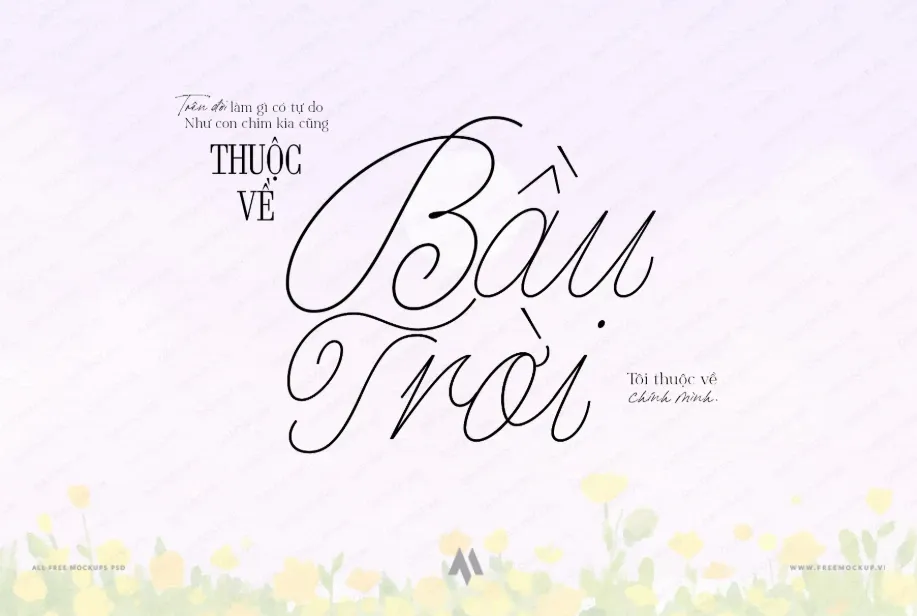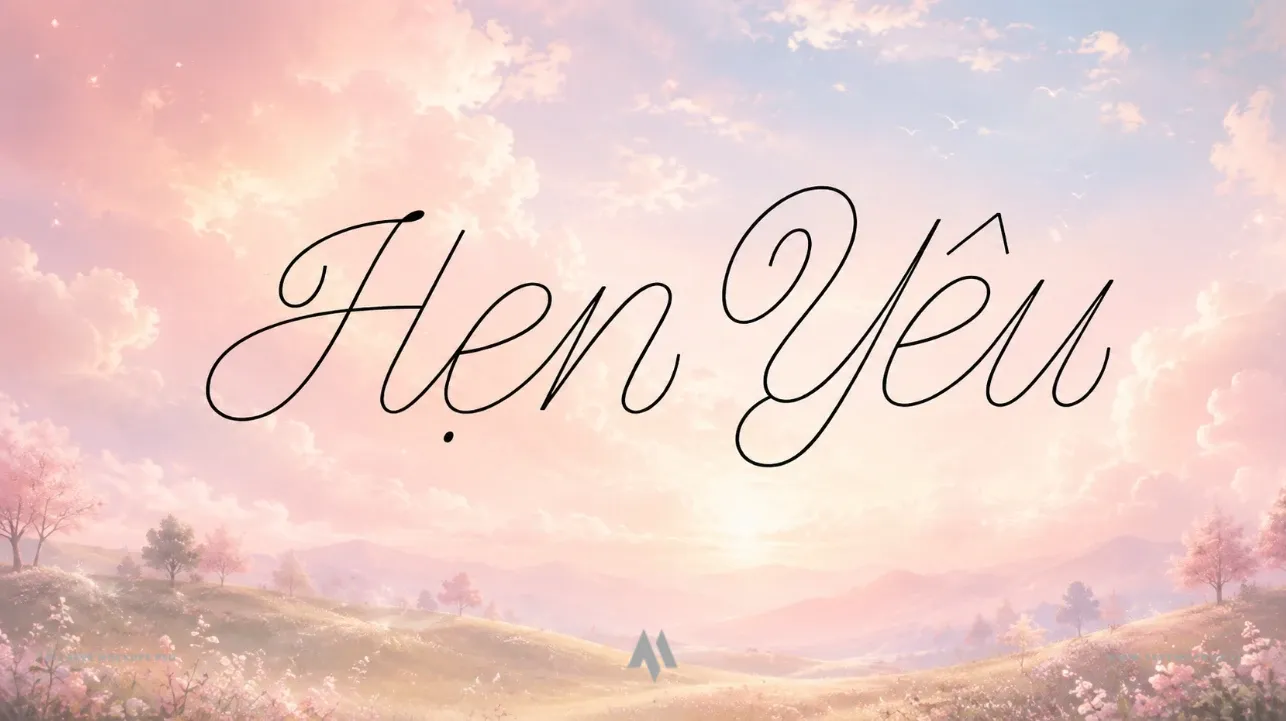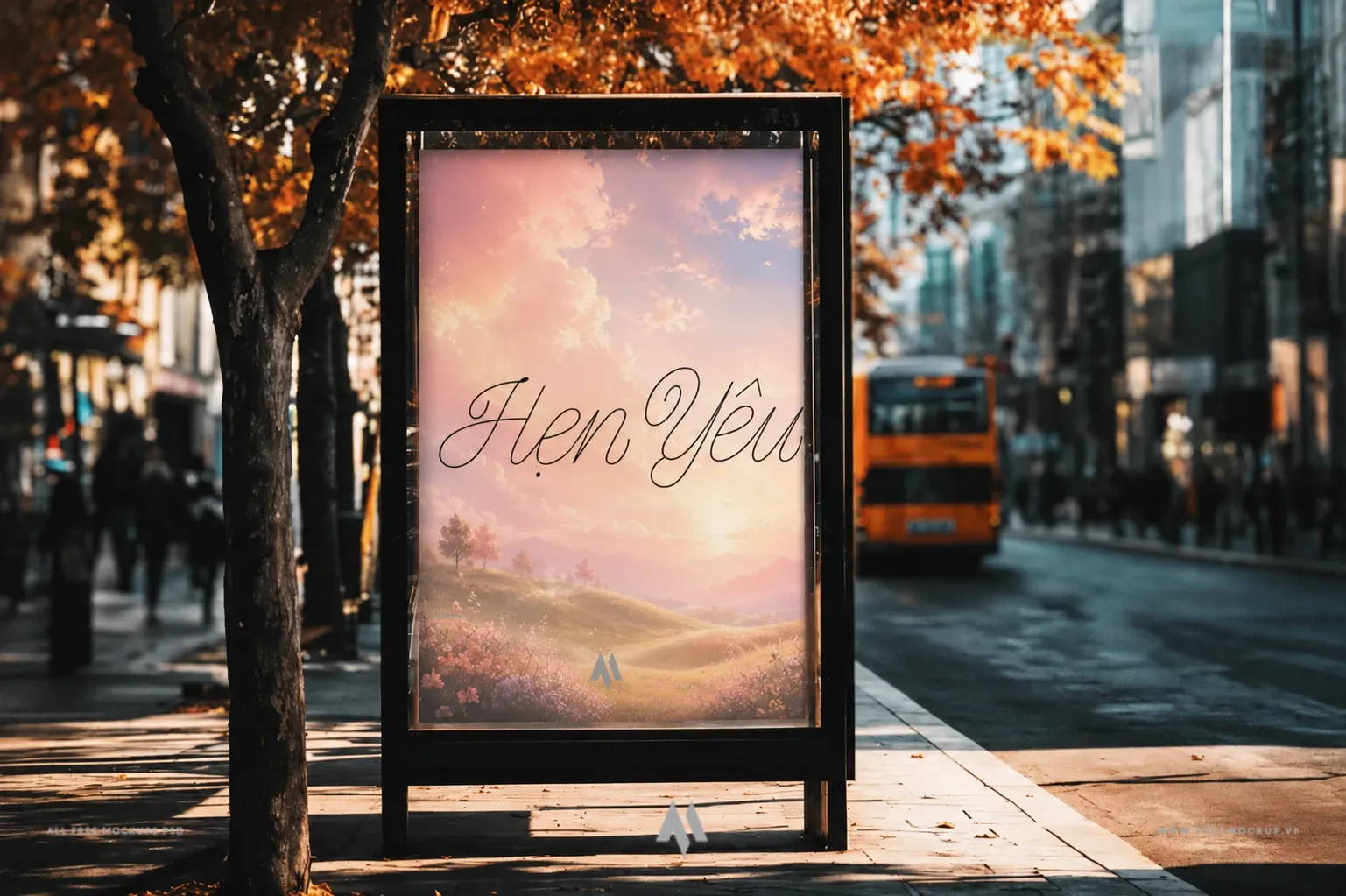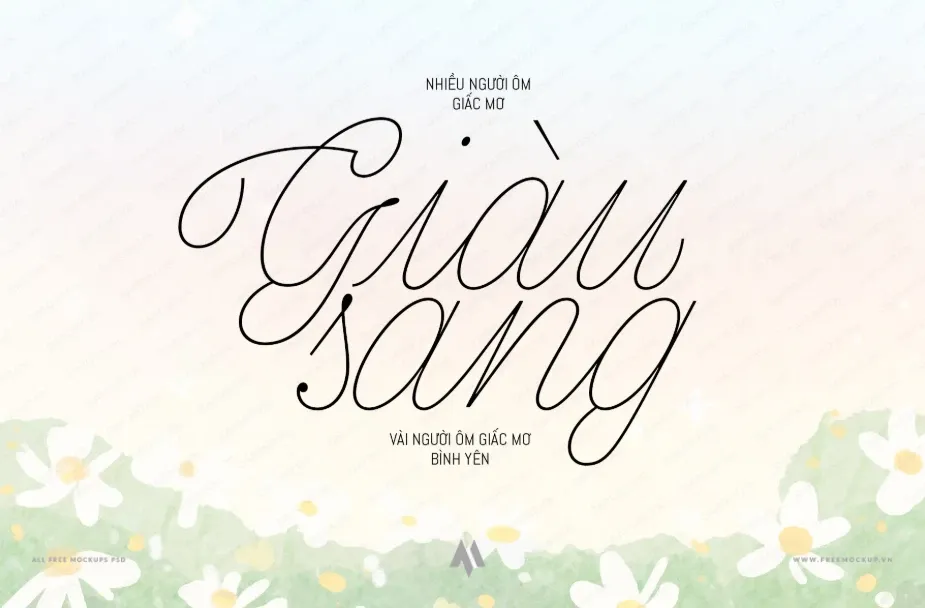
Font viết tay Việt hóa DFVN Pencerio
DFVN Pencerio Việt Hóa là bộ font chữ viết tay trang trọng (Formal Script) được thiết kế bởi xưởng font danh tiếng Indian Type Foundry. Lấy cảm hứng từ nghệ thuật thư pháp Spencerian kinh điển nhưng được cách tân độc đáo, Pencerio lược bỏ độ tương phản dày – mỏng truyền thống để thay bằng các đường nét thanh mảnh đồng nhất, mang đến vẻ đẹp vừa quý phái, chuẩn mực vừa tinh tế và hiện đại.
Đặc điểm nổi bật
• Nét bút Spencerian cách tân: Khác biệt với kiểu chữ ngòi nhọn truyền thống, Pencerio sử dụng các nét mỏng đều đặn như sợi tóc (monoline), tạo nên diện mạo thanh thoát, nhẹ nhàng nhưng vẫn giữ trọn cấu trúc trang trọng.
• Tỷ lệ x-height nổi bật: Chiều cao thân chữ thường (x-height) lớn kết hợp cùng các nét hoa uốn lượn bay bổng vượt trên nét vươn (ascender), giúp tối ưu khả năng nhận diện ký tự mà vẫn đảm bảo tính nghệ thuật.
Ứng dụng hoàn hảo trong thiết kế